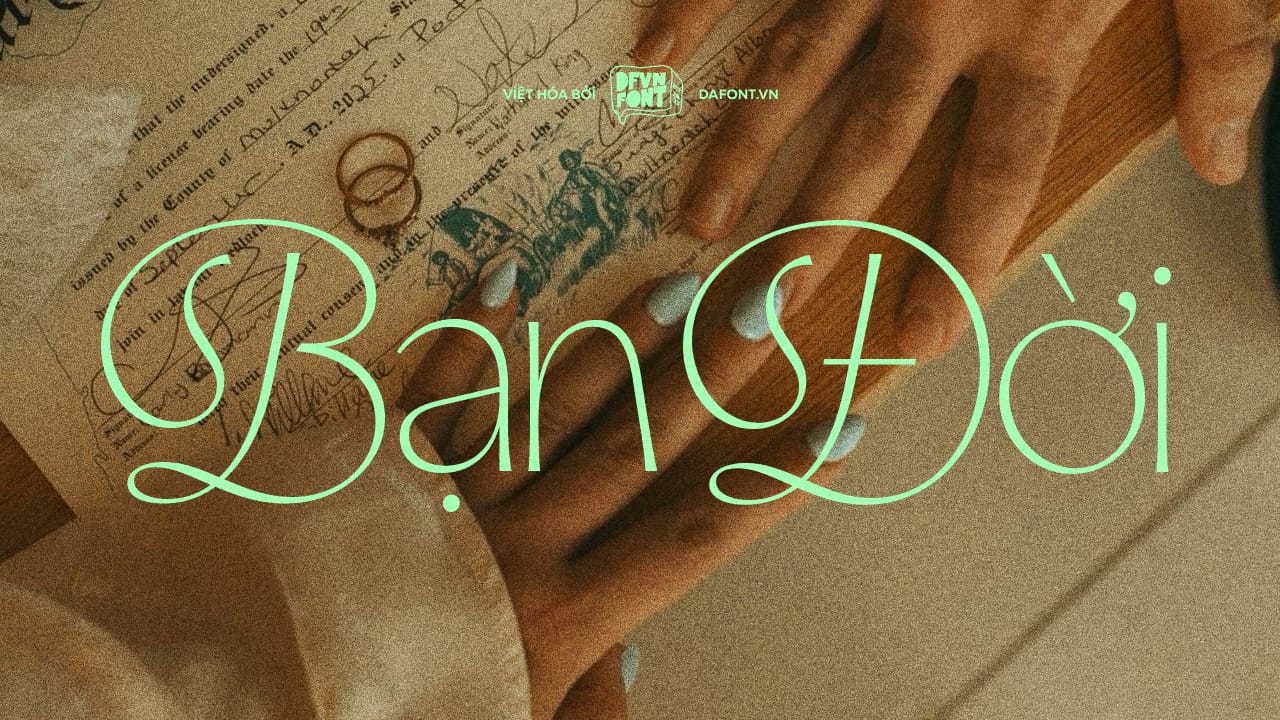
Font VIP Việt hóa là một bộ sưu tập phông chữ cao cấp, được tuyển chọn và Việt hóa tỉ mỉ để phù hợp với ngôn ngữ và thẩm mỹ của người Việt. Các font này thường có thiết kế độc đáo, mang đến sự sang trọng và chuyên nghiệp cho các dự án thiết kế.
DFVN Aespira Việt hóa – Kiểu chữ mới lạ và độc đáo
DFVN Aespira là một display typeface lấy cảm hứng từ chữ La Mã cổ điển, kết hợp cấu trúc lịch sử với các đường nét hiện đại để tạo cảm giác trang trọng nhưng giàu chuyển động, đặc biệt nổi bật ở kiểu Italic “đậm chất serif”. Tuy nhiên, Aespira không chỉ đơn thuần là...
Trọn bộ Hagrid Font Family Việt hóa (24 font)
Hagrid Font Family kiểu chữ mật mã (Crypto-typography), nhà thiết kế Cosimo Lorenzo Pancini đã tạo ra kiểu chữ độc đáo này và đặt tên là Hagrid theo tên người khổng lồ được RK Rowling mô tả trong sách Harry Potter. Hagrid là một bộ font chữ được thiết kế cho việc sử dụng trong...
Bluestar Việt hóa (10 font) – Font viết tay siêu xịn
Bluestar là một kiểu chữ viết tay tròn với nét hiện đại. Các nét chữ ở đầu được thiết kế tròn và độ tương phản ấn tượng (độ tương phản là sự khác biệt giữa phần dày và phần mỏng của nét chữ và tạo ra góc nhấn trong thiết kế kiểu chữ). Tổng cộng...
Font việt hóa BN Equipt – Kiểu chữ siêu độc đáo
BN Equipt là một kiểu chữ sans serif siêu độc đáo chứa đầy các ký tự thay thế và được thiết kế nét đậm. Các ký tự thường và ký tự in hoa nổi bật với các nét chữ vừa vuông vức vừa mềm mại. Font chữ này phù hợp để sử dụng làm tiêu...
DFVN Trixy Việt hóa (10 font)
DFVN Trixy là bộ font serif condensed Việt hóa, được thiết kế cho typography display rất nổi bật với 10 style, phù hợp cho branding, editorial, packaging và poster hiện đại mang hơi hướng retro. Trixy font – Cảm hứng từ ký ức Xô Viết Trixy là typeface serif condensed (chữ có chân dạng hẹp)...
DFVN Britti Sans Việt hóa (14 font)
DFVN Britti Sans là một bộ chữ sans-serif kiểu neo-grotesque hiện đại với đường nét hình học tinh gọn, bao gồm 14 kiểu chữ phù hợp cả tiêu đề lẫn nội dung dài trong in ấn và giao diện số. Britti Sans chịu ảnh hưởng nguyên tắc thiết kế công nghiệp và tinh thần Swiss...
DFVN Neue Kaine Việt hóa (7 font)
DFVN Neue Kaine bộ font chữ sans-serif hiện đại Neue Kaine là một font chữ sans-serif được phát triển bởi Oszkár Sztanyó, một sinh viên tại Media Design Institute, như một dự án đại học. Font này nổi bật với thiết kế công nghiệp, đường nét sạch sẽ và phong cách tối giản, phù hợp...
DFVN Picaresk Việt hóa (12 font)
DFVN Picaresk font: Kiểu chữ grotesque độc đáo lấy cảm hứng từ kiểu chữ Egyptian thế kỷ 19 Picaresk font là một kiểu chữ grotesque độc đáo, nổi bật với sự kết hợp giữa phong cách cổ điển lấy cảm hứng từ các kiểu chữ Egyptian thế kỷ 19 và các nét hiện đại không...
DFVN Malinton Việt hóa (9 font)
DFVN Malinton: Bộ font chữ sans serif đa năng cho thiết kế sáng tạo Bộ font Malinton là một lựa chọn lý tưởng cho các nhà thiết kế đang tìm kiếm một font chữ sans serif đa năng, kết hợp giữa vẻ đẹp thẩm mỹ và tính ứng dụng cao. Với 9 độ đậm từ...
DFVN Matt Việt hóa (16 font)
DFVN Matt: Bộ font chữ sans-serif hiện đại cho thiết kế đồ họa và thương hiệu Trong thế giới thiết kế đồ họa và xây dựng thương hiệu ngày nay, việc lựa chọn một font chữ phù hợp không chỉ là vấn đề thẩm mỹ mà còn là cách để tạo nên sự khác biệt....
DFVN Ogg Việt hóa (10 font)
Ogg Font Family: Kiệt tác giao thoa giữa nghệ thuật thư pháp và kiểu chữ hiện đại DFVN Ogg font là một biểu tượng độc đáo trong làng thiết kế chữ hiện đại, được truyền cảm hứng từ chữ viết tay tinh tế của nhà thiết kế sách và nghệ nhân thư pháp huyền thoại...
DFVN Youth Việt hóa (12 font)
DFVN Youth – Font chữ hiện đại mang tính biểu tượng Bộ font Youth, được phát triển bởi AllCaps, là một sản phẩm nổi bật trong thế giới thiết kế chữ hiện đại. Được lấy cảm hứng từ phong cách Bauhaus và thời kỳ dàn chữ quang học (phototypesetting), Youth mang đến một diện mạo...
DFVN Gustavo Việt hóa (10 font)
Gustavo font là bộ font sans serif hình học, mang đến sự hiện đại và tinh tế cho mọi dự án thiết kế. Ra mắt vào năm 2018, Gustavo đã trở thành bộ font nhờ vẻ đẹp cổ điển pha chút phá cách. Bộ font này bao gồm 10 kiểu và một bộ biểu tượng...
DFVN The Seasons Việt hóa (6 font)
Nếu bạn đang tìm kiếm một font serif mang lại vẻ cổ điển và sự thanh lịch, font The Seasons là sự lựa chọn không thể bỏ qua. Với thiết kế tinh tế, sự kết hợp giữa nét cổ điển và hiện đại, The Seasons là một bộ font lý tưởng cho các dự án...
DFVN Monument Extended Việt hóa (18 font)
Monument Extended là một font chữ sans-serif với các ký tự được mở rộng (extended typeface) Những ký tự này có dạng hình học và đường nét sắc sảo, mang lại ấn tượng mạnh mẽ trong bất kỳ thiết kế nào. Font chữ này cân bằng giữa tính hiện đại và sự thanh lịch vượt...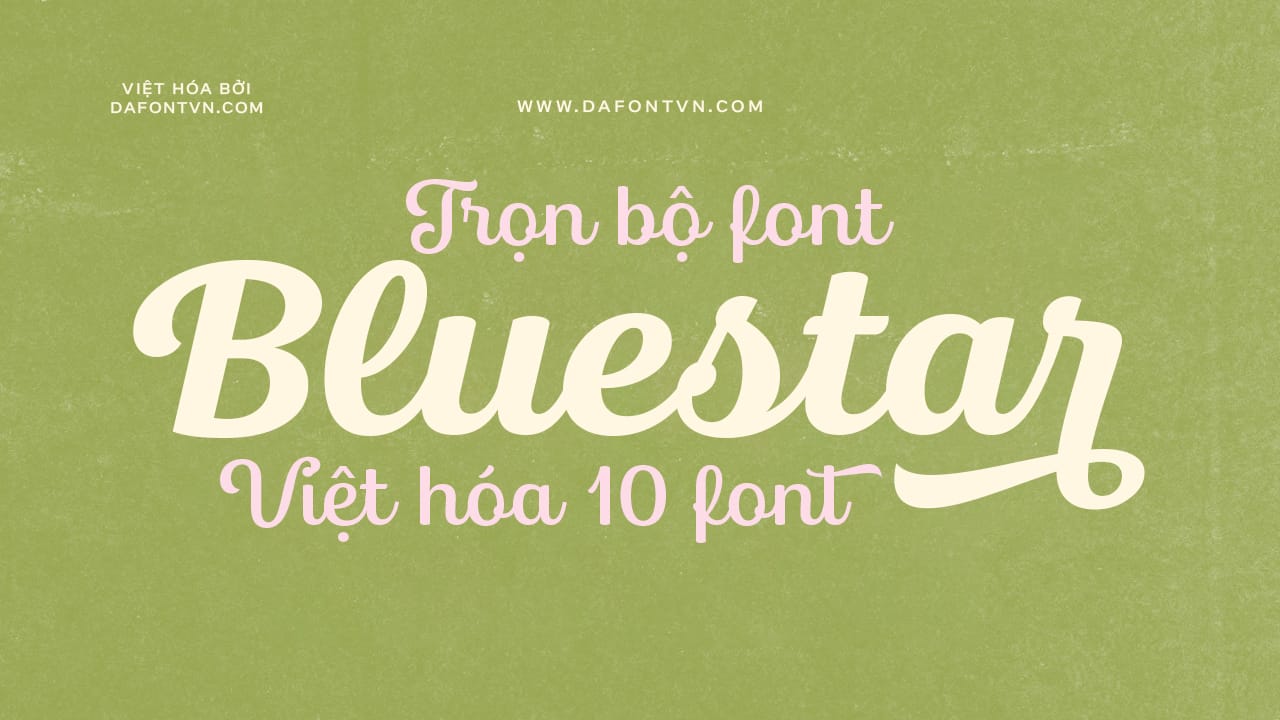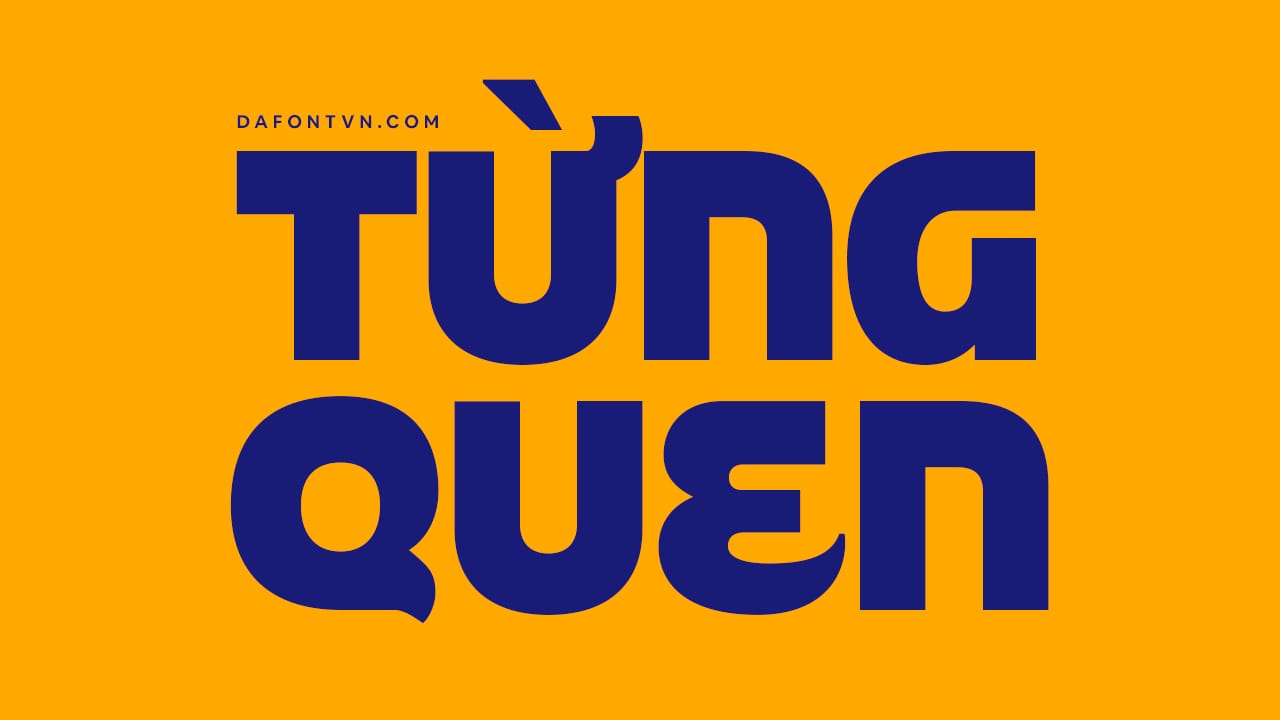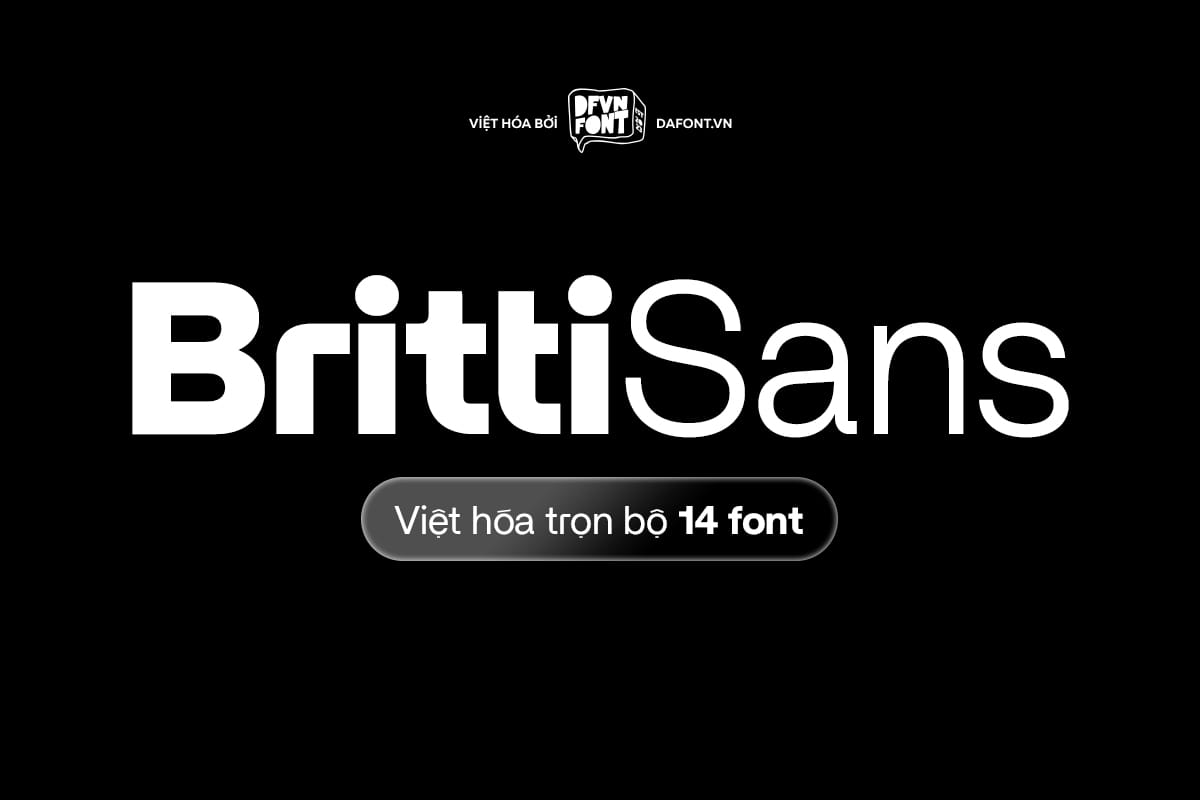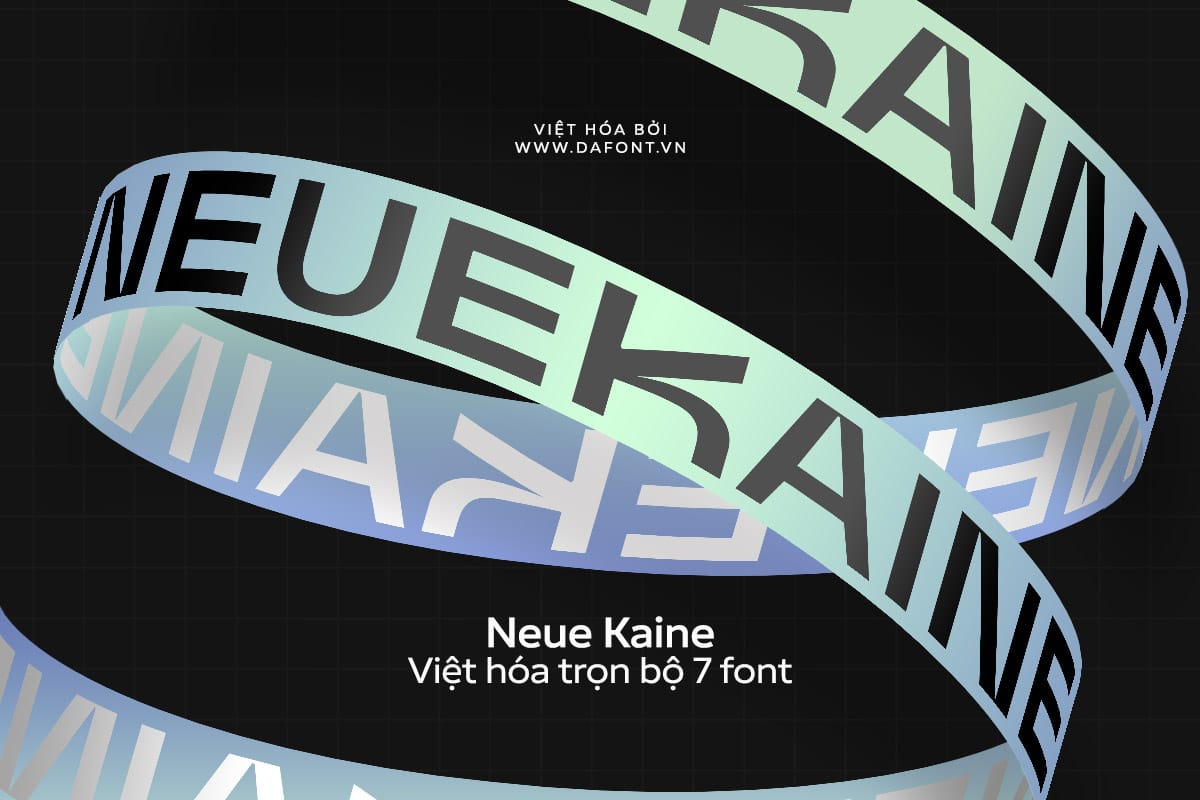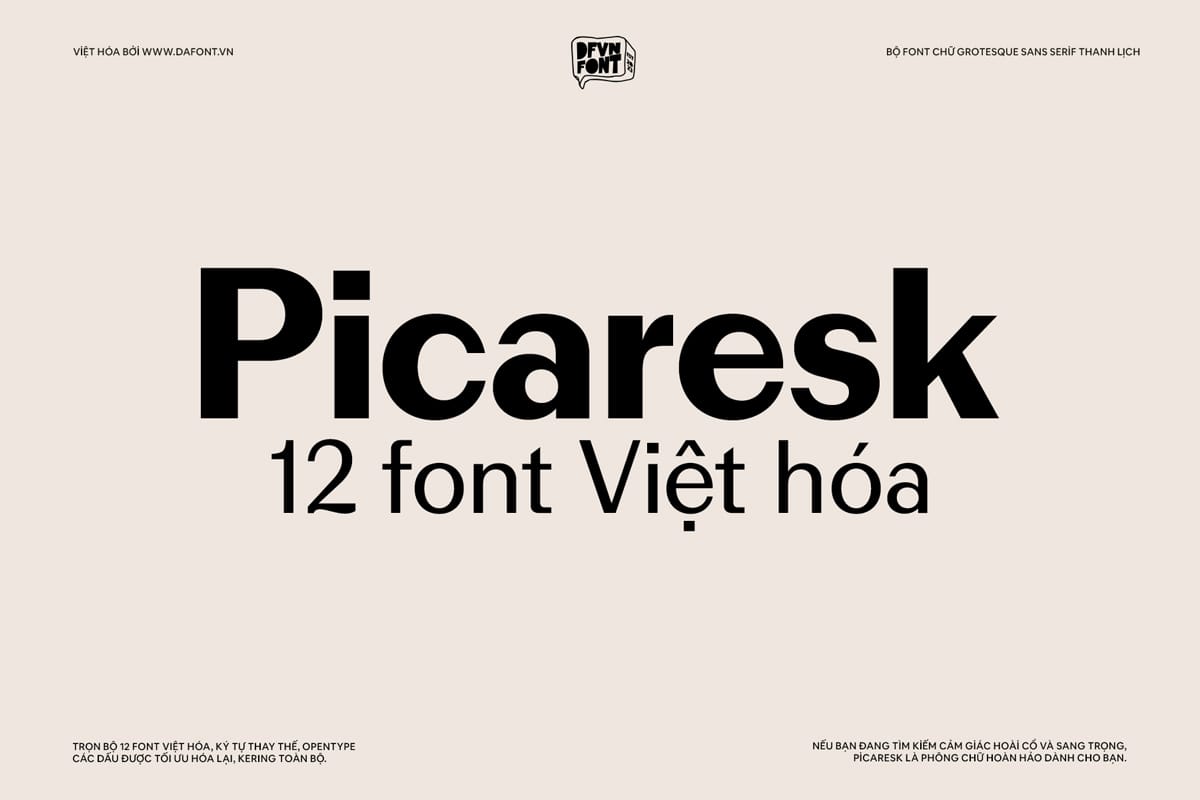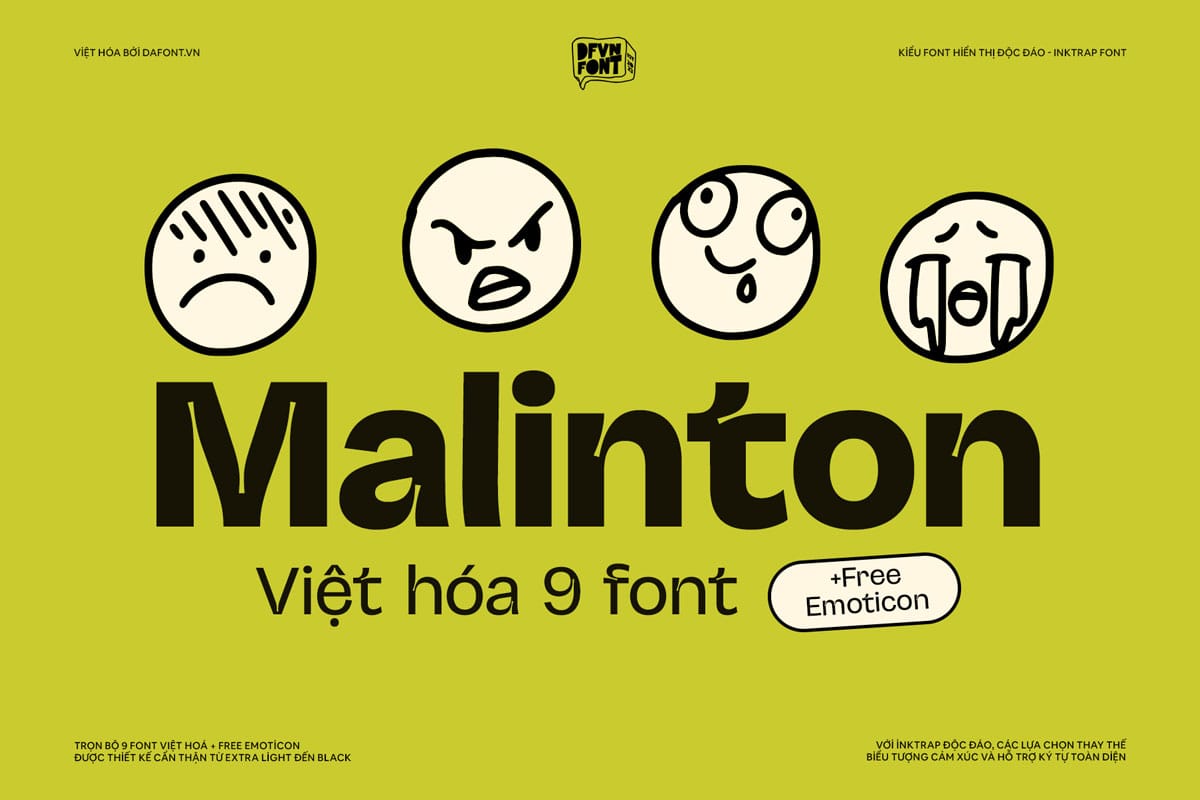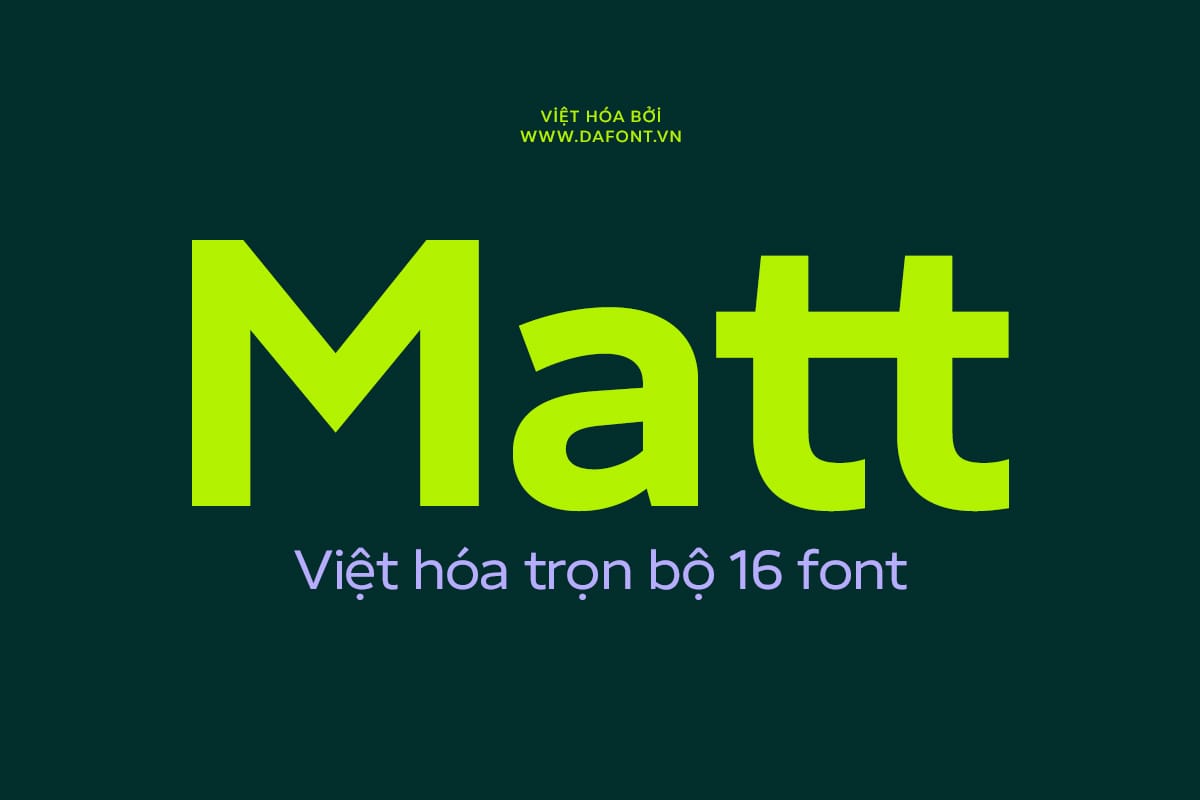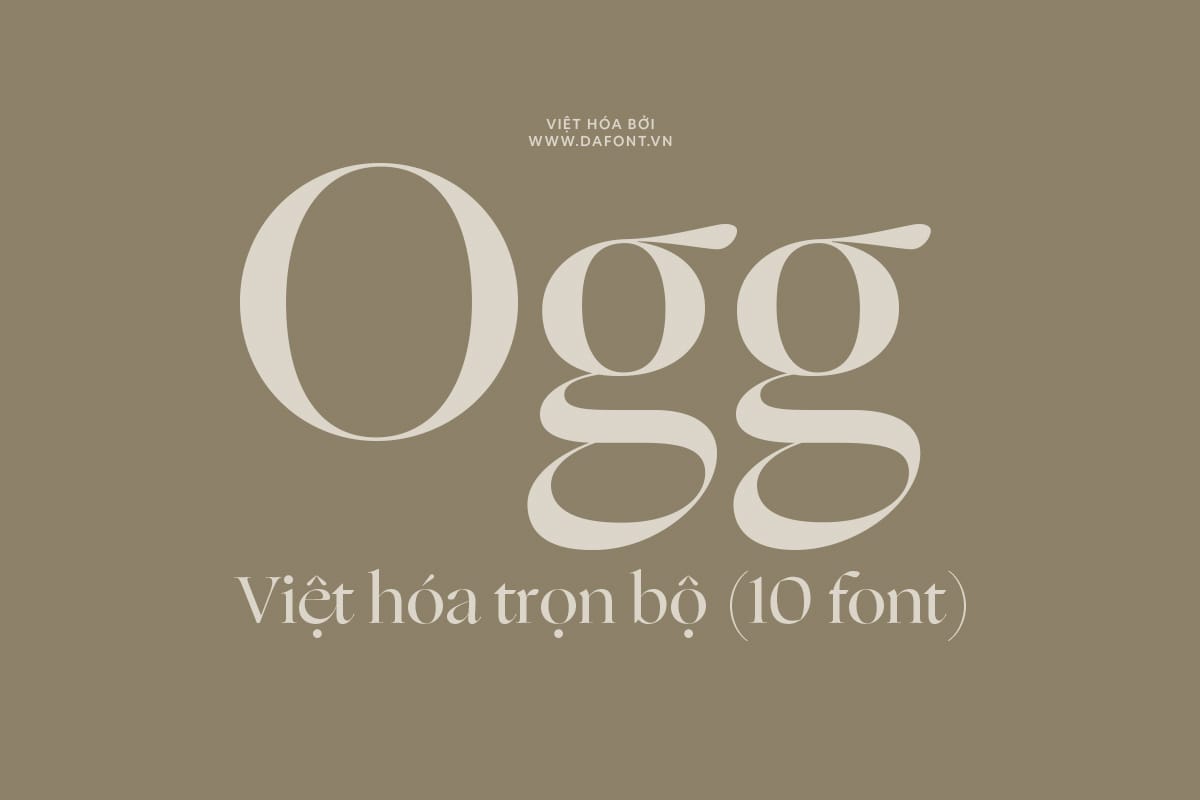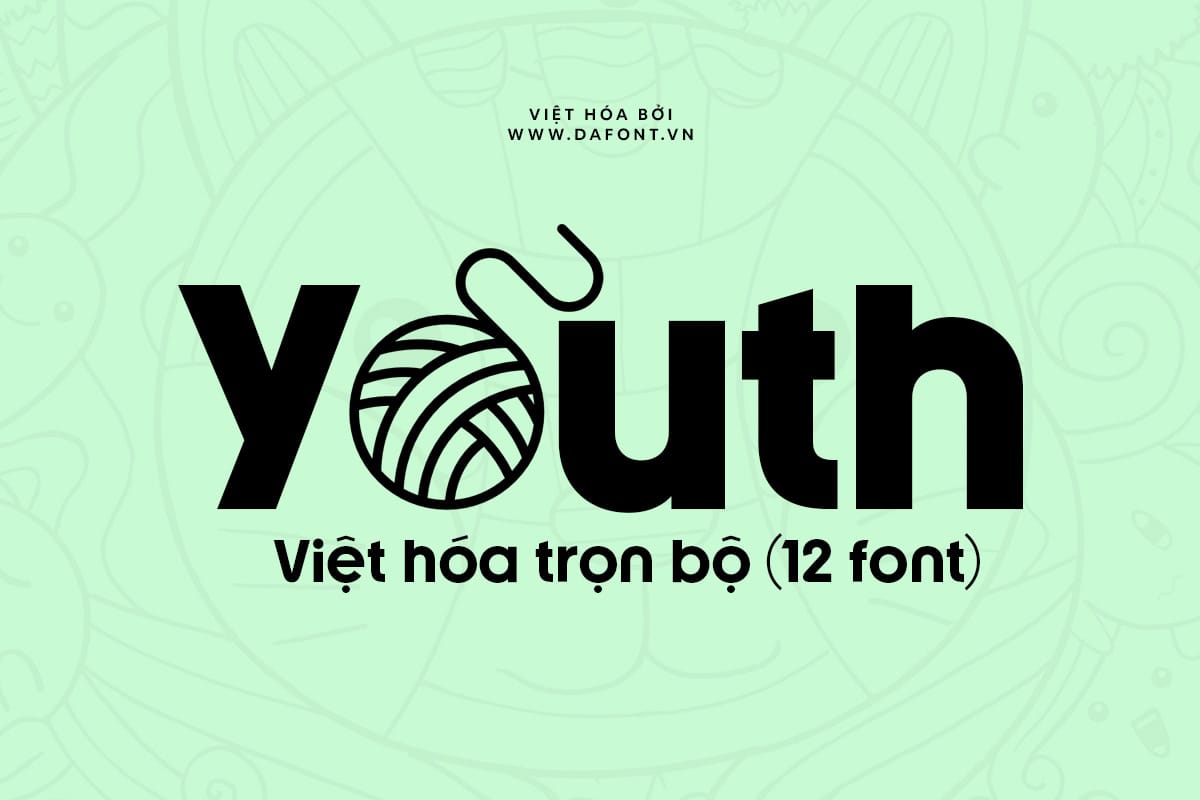